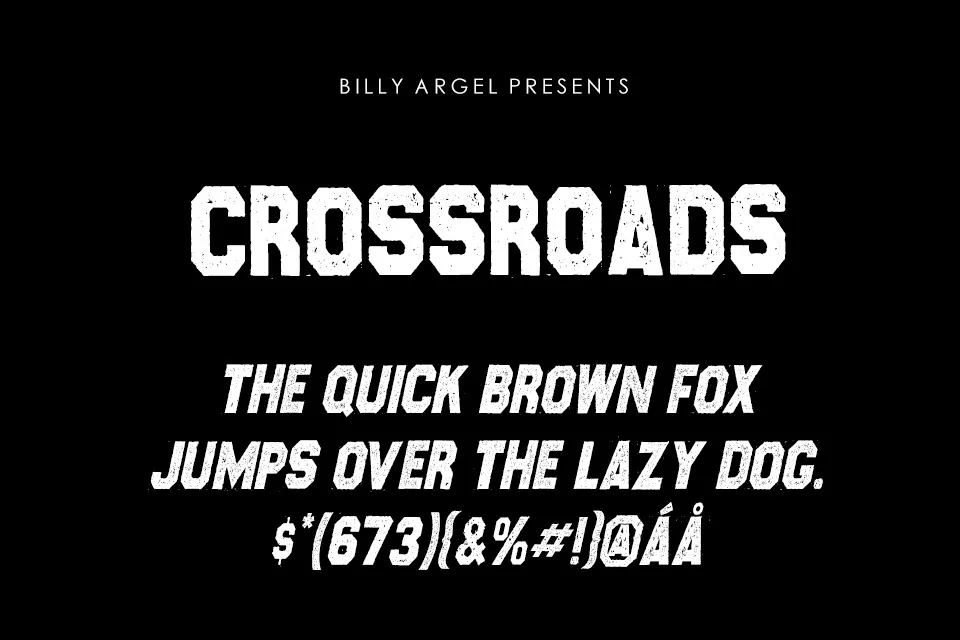
Crossroads Font é uma elegante novidade no mundo dos tipos de letra de display, lançada pelo 99designs. Este tipo de letra sans serif não apenas se destaca por sua aparência contemporânea e moderna, mas também oferece um estilo inovador que desafia o tradicional. Inspirado na estética atual do design, esta fonte foi criada para atender às necessidades de inúmeros conceitos e ideias que surgem nesta era moderna. Com uma identidade única que combina sofisticação com originalidade, Crossroads Font é ideal para criar um impacto visual forte em qualquer projeto gráfico ou design digital. Para designers buscando algo diferente e atual no seu trabalho, este é um excelente adicional à sua biblioteca de tipos de letra.